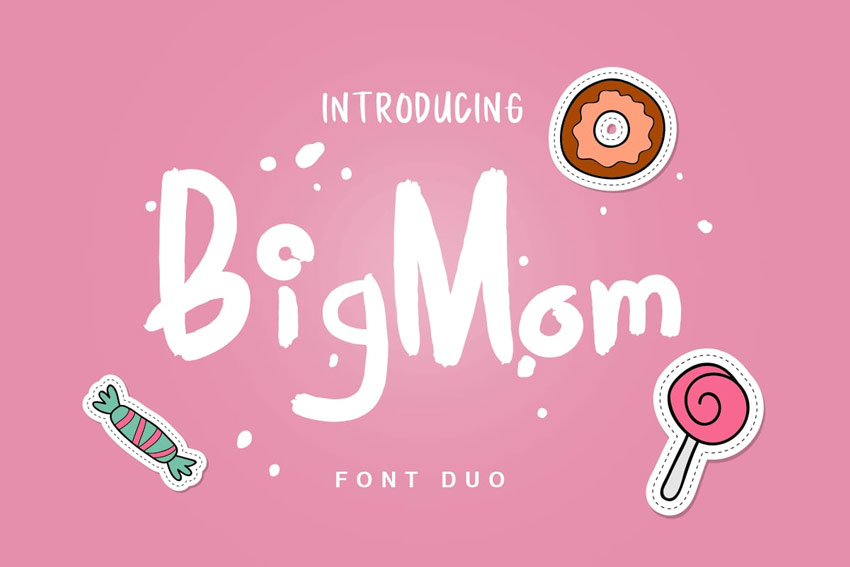
Nama Font Canva Aesthetic. Salah satunya adalah aplikasi canva. Terkadang ketika anda mencari font minimalis untuk sebuah desain, anda biasanya sudah punya tampilan atau gaya yang diinginkan.
Tapi di lain waktu, anda hanya menginginkan sesuatu yang sederhana, bersih dan modern. Hipfonts is a design collective focused on promoting and showcasing typefaces created by independent creatives around the world. It’s important to note that even though i’ve provided a list of canva free fonts, the free options are more.
Best canva font pairings & combinations. Di sini kita bisa membuat desain dengan estetik menggunakan template, elemen, font dan fitur lainnya. Ditambah dengan kreatifitas memutar dan memisahkan detailnya font dapat memiliki nuansa keren dan kontemporer.
Rekomendasi Font Aesthetic Free Di Canva.
Selain itu, font ini juga dapat digunakan secara gratis, baik untuk personal atau kebutuhan lainnya. Tetapi, font juga memiliki arti mendalam yang bisa menunjukan bagaimana karakter sebuah video. Berdasarkan garis dan bentuk geometris, font modern bersih, jelas, dan mudah dibaca;
Rekomendasi Nama Font Aesthetic Pertama Dari Kami Adalah Lombok.
Tapi, ada beberapa hal yang perlu diperhatikan sebelum memilih font. The best handwriting fonts availabe in canva free and pro the best modern brand fonts on canva. Dengan menggunakan font yang kami rekomendasikan, desain situs anda dapat ditingkatkan, dan konten anda menjadi lebih mudah dibaca.
Ada Beberapa Nama Font Aesthetic Yang Bisa Anda Gunakan Untuk Membuat Berbagai Proyek Desain Menjadi Semakin Unik.